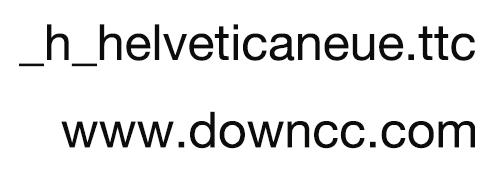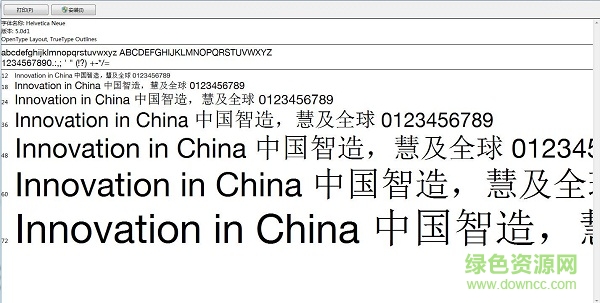
_h_helveticaneue.ttc字體是一款蘋果系統(tǒng)字體,風(fēng)格簡潔,干凈理性,ps里面也有_h_helveticaneue字體,該字體的安卓版本和類似字體本站也有提供,歡迎免費(fèi)下載!
1.非常緊湊的字間距、比較高的x高度;
2.簡潔清晰、平衡冷靜;
3.字體的結(jié)構(gòu)嚴(yán)謹(jǐn)、可讀性強(qiáng)。